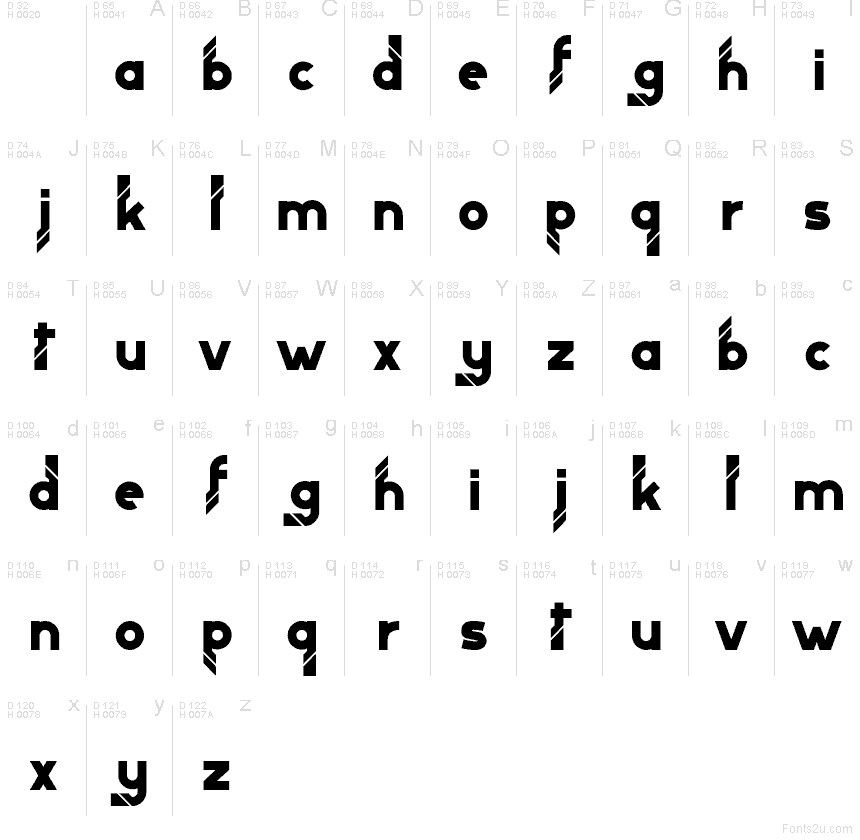
Schacher Chess od Vladimíra Nikoliče je bezplatné geometrické display písmo bez patek s širokými, těžkými písmeny a kompaktní siluetou. Zaoblené tahy se setkávají s rovnými řezy a dodávají písmu robustní, konstruovaný vzhled. Úzké prostrkání a téměř kruhové tvary vytvářejí hutnou texturu, kterou umocňují opakující se diagonální zářezy.
Obaly deskových her těží z jeho pevných grafických tvarů. Stejná bloková geometrie se hodí pro branding šachových klubů, turnajové plakáty a herní merchandise, čímž tyto oblasti propojuje prostřednictvím témat strategie a soutěživosti.